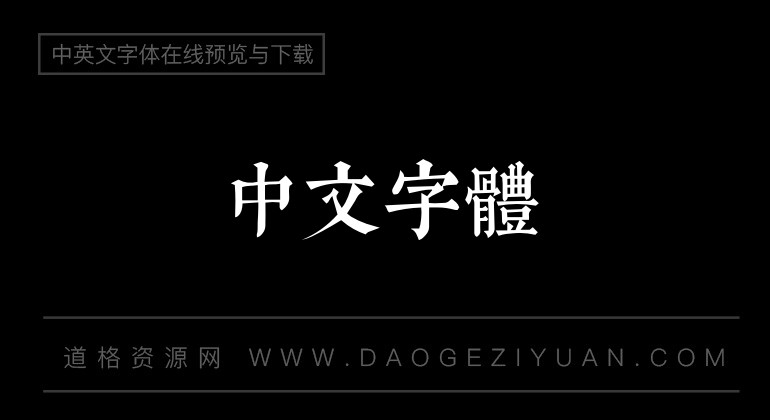
文悦古典明朝体
文悦古典明朝体是一款古典风格的字体,它采用了明朝的字体风格,运用了精致的线条和折线,增加了字体的细节,使字体看起来更加精致,更有深度。它的特点是古典,曲线优美,结构紧凑,字形稳定,字体精致,更有深度,更有层次感,易于阅读。它适用于各种文字、书法、图片、标志等场景,可以为文字增添古典气息,使文字更有质感。
文悦古典明朝体是一款非常不错的手写艺术字体,具有很好的视觉感,适合于文化类的宣传设计、商业类品牌的广告和产品包装设计以及个性化文字排版等较多场景。